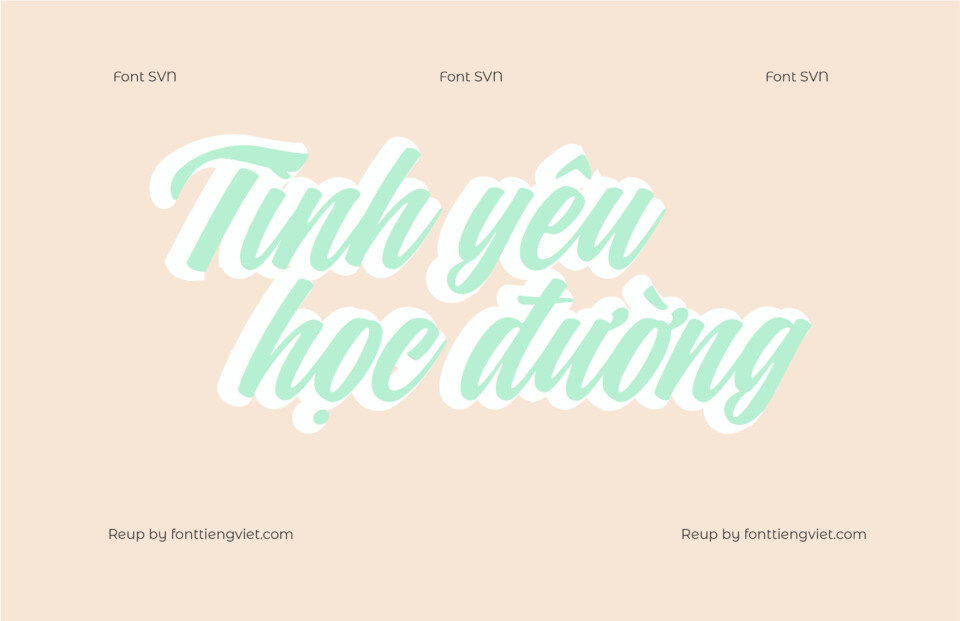
Font Việt hóa SVN Indie
Khám phá sức hút của Font Việt hóa SVN Indie dành cho thiết kế học đường
Giới thiệu về sức hút của Font Việt hóa SVN Indie
Trong thế giới sáng tạo, việc lựa chọn một Font Miễn Phí phù hợp chính là chìa khóa để truyền tải thông điệp hiệu quả nhất. Font Việt hóa SVN Indie nổi lên như một lựa chọn hàng đầu nhờ phong cách tự do, phóng khoáng nhưng không kém phần tinh tế. Đây là bộ font mang đậm hơi thở nghệ thuật, giúp các bài thuyết trình hay ấn phẩm trường học trở nên sinh động và gần gũi hơn với các bạn học sinh.
Đặc điểm nổi bật của Font Việt hóa SVN Indie
Nét vẽ thủ công độc đáo
Đúng như tên gọi, SVN Indie mang phong cách “Independent” với các đường nét thanh mảnh, uốn lượn tự nhiên như nét chữ viết tay. Điều này tạo cảm giác thân thiện, dễ mến ngay từ cái nhìn đầu tiên. Bộ font này cực kỳ phù hợp để thiết kế bìa sách, nhãn vở hoặc các poster sự kiện mang tính chất năng động, trẻ trung của tuổi học trò.
Tối ưu hóa hoàn toàn cho tiếng Việt
Ưu điểm lớn nhất của Font Việt hóa SVN Indie chính là hệ thống dấu câu được căn chỉnh tỉ mỉ. Bạn sẽ không còn lo lắng về lỗi font hay các dấu gạch chéo không đều khi gõ tiếng Việt. Sự đồng nhất trong thiết kế giúp văn bản luôn chuyên nghiệp và rõ ràng trên mọi thiết bị hiển thị.
Ứng dụng Font Việt hóa SVN Indie trong học tập
Các giáo viên có thể sử dụng bộ font này để làm giáo án điện tử thêm phần lôi cuốn, giúp học sinh dễ dàng tiếp thu kiến thức. Đối với các bạn học sinh, đây là công cụ tuyệt vời để trang trí nhật ký số hoặc làm báo tường điện tử. Sự kết hợp giữa tính thẩm mỹ và công năng sử dụng đã giúp SVN Indie khẳng định vị thế trong lòng người dùng Việt.